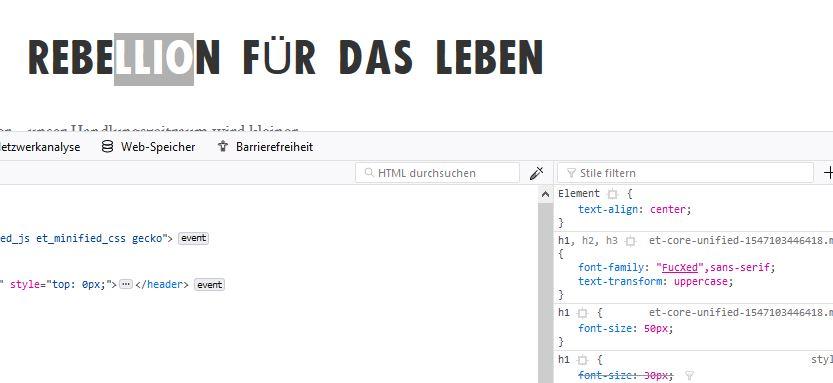
Schriftar wie FucXed
ich nehme an, dass FucXed eine Google Schriftart ist, jedenfalls finde ich diese nicht.
Könnt ihr mir bitte eine Schriftart nennen, die dieser ähnlich ist?
Sie auch hier.
Ich vermute eher, dass der Font auf der Grundlage einer schmalen Grotesk wie bspw. der Twentieth Century Pro Bold Condensed „handveredelt“  wurde. Darauf lässt zumindestens das mitteltolle Kerning und der dürftige Zeichenvorrat schliessen --> https://extinctionrebellion.de/manifest/
Was bringt Dich auf diesen Gedanken?
Dankeschön. ...Wenn ich auf der ensprechenden Seite bin und mit der rechten Maustaste
den Text markiere und das Element untersuche, steht dort diese Schriftart ..., siehe
Anhang.
Und dieser Font wird eben weder von den Google-Servern ausgeliefert noch existiert dort ein Fonts dieses Namens. Der »eigenwillige« Fontname legt nah, dass das ein Eigenbau ist. Ob auf eigenen Zeichnungen oder irgendeiner anderen Schrift basierend, weiß ich nicht. Wenn du das genau wissen willst, wirst du dich an die Websitebetreiber wenden müssen.
Pate stand vielleicht die Futura:
… die Futura Round wäre zumindest sehr ähnlich:
Hier sollte mal geklärt werden welche Schrift wirklich gemeint ist, wenn dort mehrere Schriften zu sehen sind.